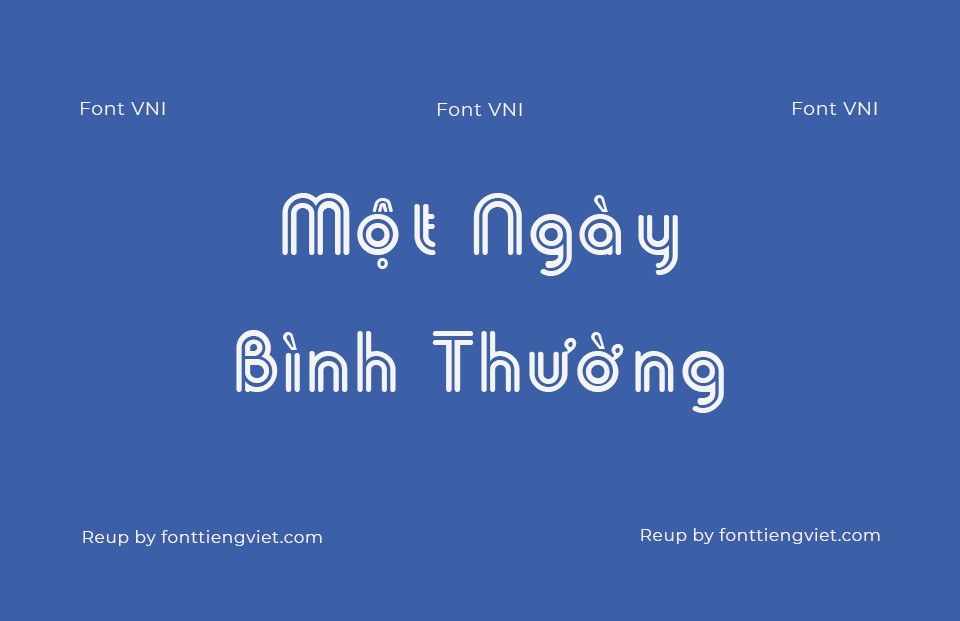
Font Việt hoá VNI Tubes
Giới thiệu về bộ Font Việt hoá VNI Tubes dành cho học tập
Trong thế giới thiết kế đồ họa, việc lựa chọn một Font Miễn Phí chất lượng đóng vai trò then chốt để tạo nên sự khác biệt cho các dự án sáng tạo. Font Việt hoá VNI Tubes là một trong những bộ phông chữ nổi bật với phong cách hiện đại, mang đậm nét bo tròn mềm mại và cấu trúc hình ống đặc trưng. Bộ font này đã được tối ưu hóa bảng mã để phù hợp với người dùng Việt Nam, giúp các bạn học sinh và giáo viên dễ dàng soạn thảo văn bản mà không lo lỗi font hay thiếu ký tự tiếng Việt có dấu. Đây là lựa chọn lý tưởng cho các bài thuyết trình, làm bìa báo tường hay thiết kế tiêu đề poster trường học.
Những đặc điểm nổi bật của Font Việt hoá VNI Tubes
Kiểu dáng sáng tạo và tính ứng dụng cao
Đặc trưng lớn nhất của Font Việt hoá VNI Tubes nằm ở các nét vẽ dày dặn, tạo cảm giác thân thiện và gần gũi. Kiểu chữ này cực kỳ phù hợp cho các thiết kế mang tính vui tươi, năng động của lứa tuổi học trò. Bạn có thể sử dụng nó để làm nổi bật các từ khóa quan trọng hoặc trang trí cho các thiệp mời sự kiện trong lớp. Nhờ độ tương phản thấp và cấu trúc hình khối rõ ràng, font chữ đảm bảo tính dễ đọc ngay cả khi nhìn từ xa trên các bảng tin lớn.
Để đạt được hiệu ứng thẩm mỹ tốt nhất, bạn nên kết hợp font chữ này với các tông màu sáng hoặc sử dụng đổ bóng để tạo chiều sâu. Việc ứng dụng phông chữ vào thực tế sẽ giúp các bài báo cáo trở nên sinh động và chuyên nghiệp hơn rất nhiều. Nếu bạn đang tìm kiếm một bộ chữ vừa lạ mắt vừa đầy đủ tính năng, đừng bỏ qua cơ hội trải nghiệm Font Miễn Phí, Font Việt Hóa, Font Việt hoá VNI Tubes để làm mới không gian học tập và sáng tạo của mình ngay hôm nay.